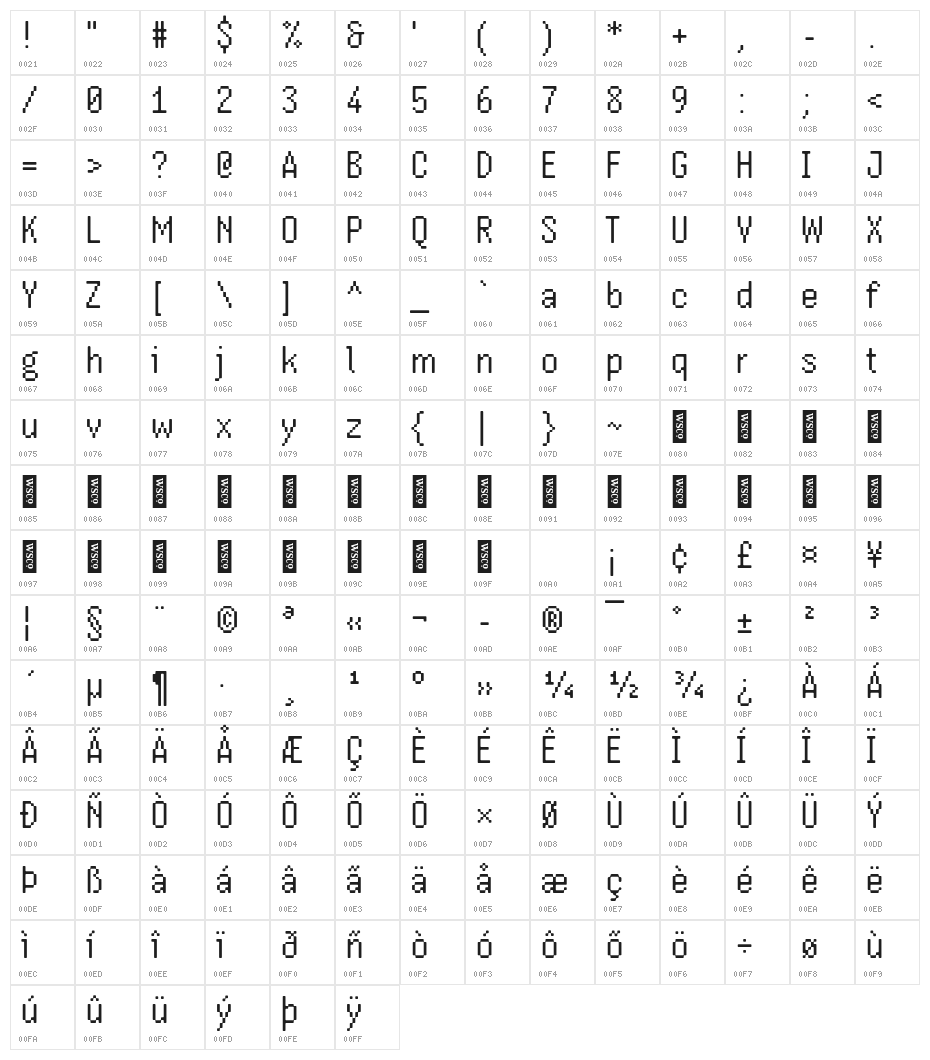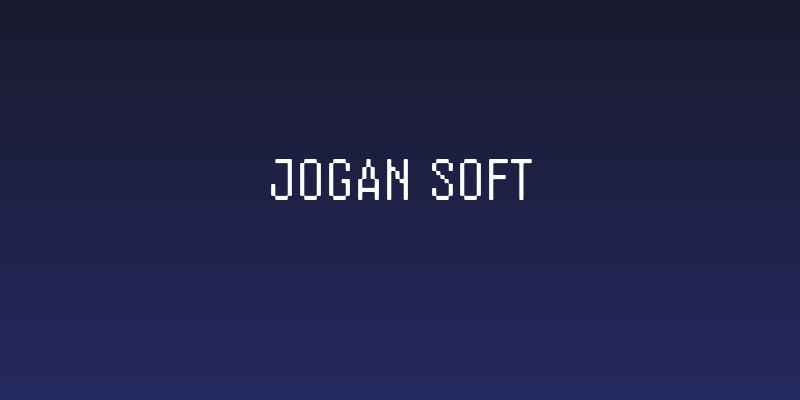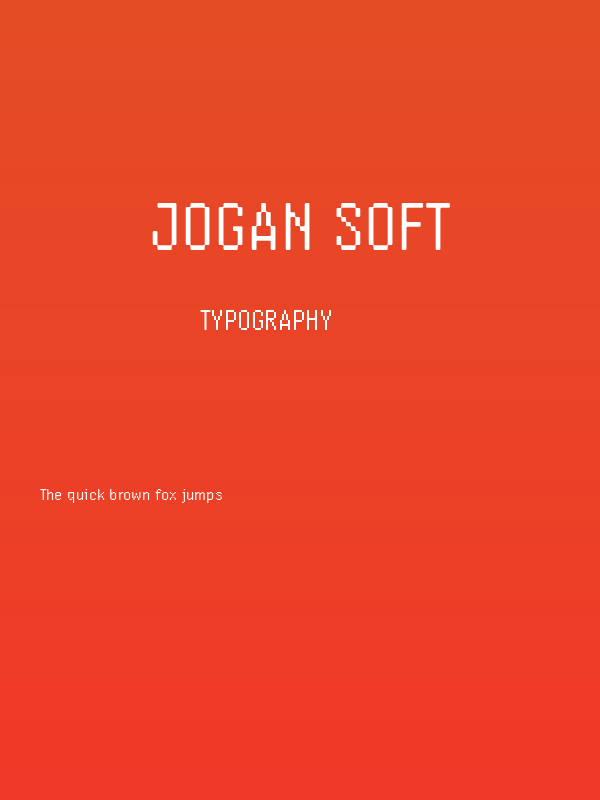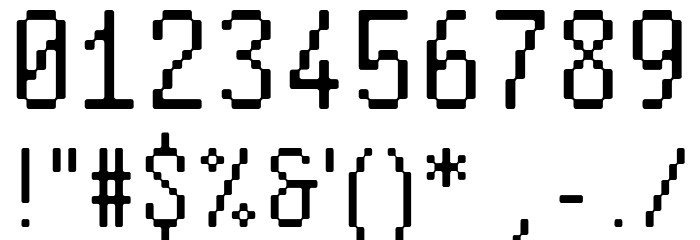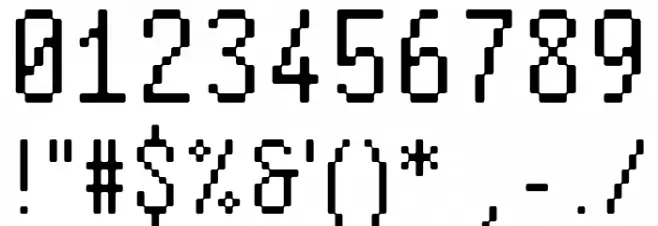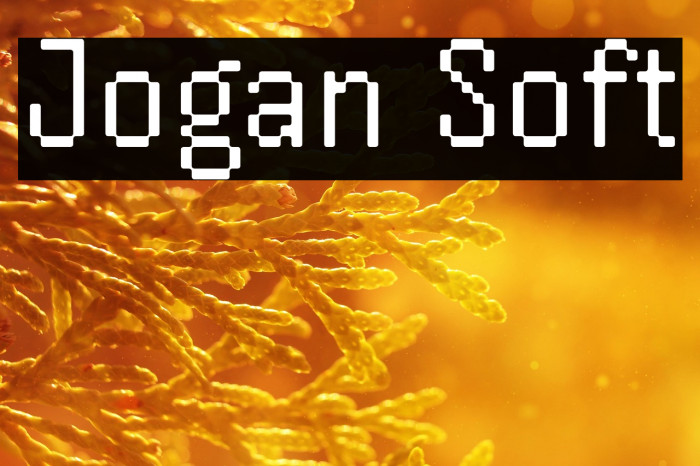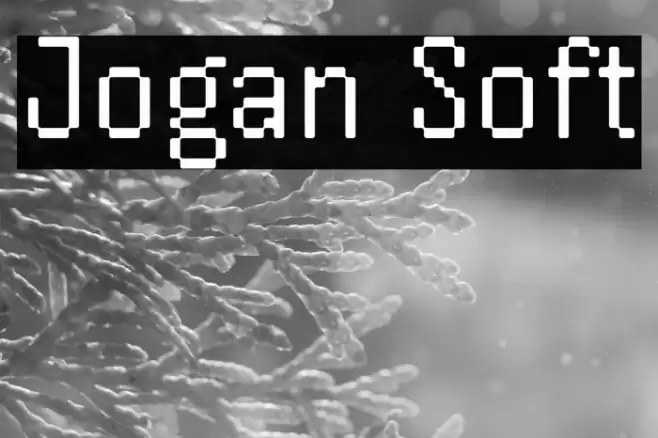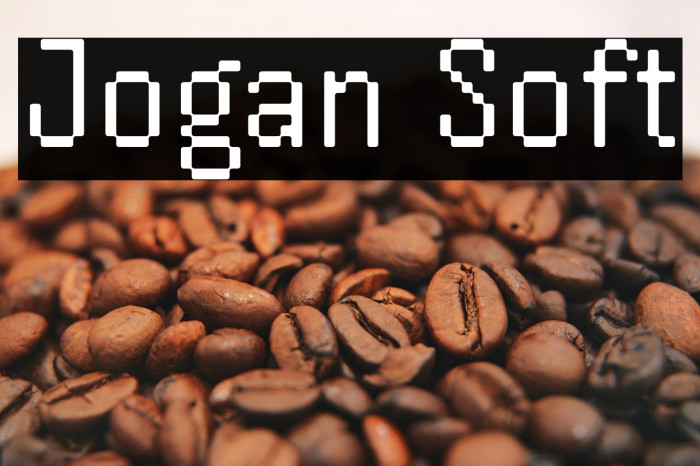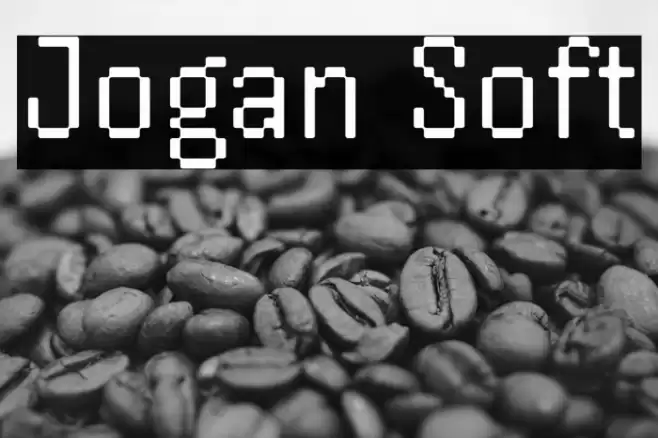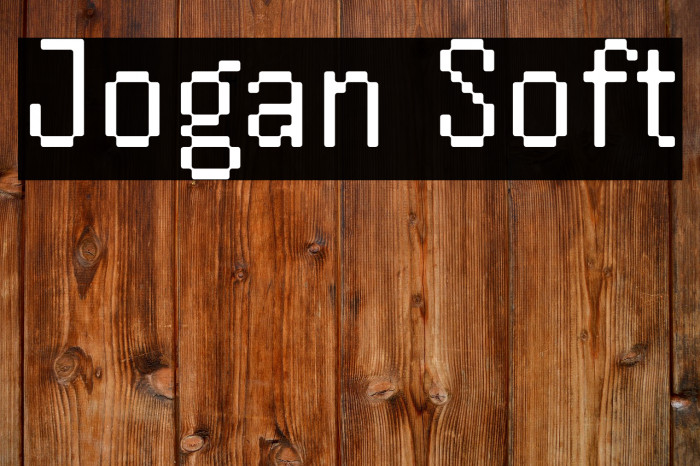
Jogan Soft Font
✎ Pixel
| Kategorien | Pixel |
| Gesamtstil | Retro, Digital |
| Anwendungsfall | Logos, Digital displays, Coding interfaces |
| Vorgeschlagene Projekte | Ideal for retro video games, tech-themed designs, digital art projects, and coding interfaces. |